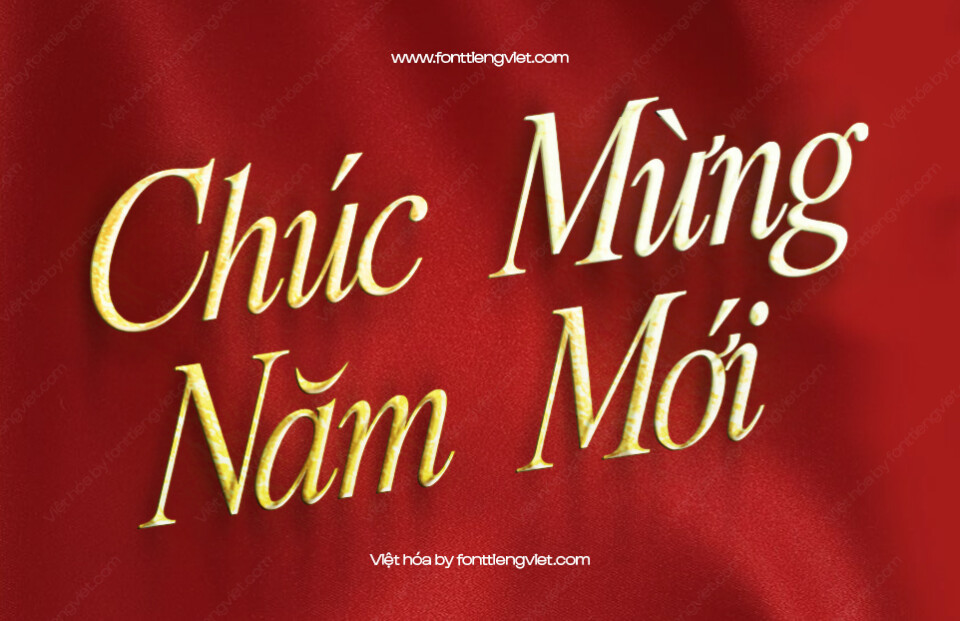
Font Việt hóa 1FTV VIP Relationship Of Mélodrame – Tết
Giới thiệu bộ Font Việt hóa 1FTV VIP Relationship Of Mélodrame – Tết
Chào mừng bạn đến với thế giới sáng tạo của những con chữ đầy nghệ thuật và cảm xúc. Trong không khí rộn ràng chuẩn bị cho mùa xuân mới, nhu cầu tìm kiếm những bộ Font Miễn Phí chất lượng cao luôn là ưu tiên hàng đầu của các nhà thiết kế đồ họa. Bộ Font Việt hóa 1FTV VIP Relationship Of Mélodrame – Tết chính là món quà đặc biệt dành riêng cho cộng đồng thiết kế Việt Nam. Đây không chỉ là một phông chữ thông thường mà là sự kết hợp hoàn hảo giữa nét cổ điển thanh lịch và tinh thần hiện đại đầy sức sống. Với các đường nét được chăm chút tỉ mỉ, bộ font này giúp truyền tải thông điệp về sự gắn kết, tình yêu và những giá trị truyền thống tốt đẹp trong dịp Tết Nguyên Đán.
Đặc điểm nổi bật của Font Việt hóa 1FTV VIP Relationship Of Mélodrame – Tết
Thiết kế sang trọng và mang tính biểu tượng
Bộ Font Việt hóa 1FTV VIP Relationship Of Mélodrame – Tết sở hữu cấu trúc chữ cái mảnh mai nhưng vô cùng chắc chắn, tạo nên một cảm giác sang trọng (VIP) ngay từ cái nhìn đầu tiên. Các ký tự được thiết kế với độ tương phản cao, mô phỏng phong cách Mélodrame đầy kịch tính và lãng mạn. Điều này giúp bộ font trở nên cực kỳ nổi bật trên các ấn phẩm truyền thông như poster sự kiện, bìa tạp chí hoặc các thiệp chúc mừng năm mới. Đặc biệt, các dấu câu tiếng Việt đã được tinh chỉnh lại một cách khéo léo, đảm bảo không bị lỗi font khi gõ văn bản dài, giúp quy trình làm việc của bạn trở nên trơn tru và chuyên nghiệp hơn bao giờ hết.
Tính ứng dụng đa dạng trong mùa lễ hội
Khả năng thích ứng của Font Việt hóa 1FTV VIP Relationship Of Mélodrame – Tết là rất ấn tượng. Bạn có thể sử dụng nó cho các tiêu đề chính của banner quảng cáo Tết, các bao lì xì mang phong cách tối giản hay thậm chí là các video giới thiệu sản phẩm xuân. Font chữ này mang lại sự hài hòa khi kết hợp với các gam màu truyền thống như đỏ, vàng và xanh lá, tạo nên một không gian thị giác ấm cúng và đoàn viên. Sự tinh tế trong từng nét chữ giúp người xem cảm nhận được sự chân thành và tinh thần gắn kết đúng như tên gọi Relationship của bộ phông chữ này.
Hướng dẫn sử dụng và tối ưu thiết kế với font chữ Tết
Cách phối hợp màu sắc và bố cục
Để phát huy tối đa vẻ đẹp của Font Việt hóa 1FTV VIP Relationship Of Mélodrame – Tết, bạn nên ưu tiên các bố cục thoáng đãng và sử dụng khoảng trắng thông minh. Việc đặt font chữ này lên các nền hình ảnh có độ chi tiết thấp sẽ giúp các nét chữ thanh mảnh được hiển thị rõ nét nhất. Đối với các thiết kế in ấn, hãy thử sử dụng kỹ thuật ép kim hoặc phủ UV trên các ký tự chính để tạo hiệu ứng thị giác đẳng cấp. Đừng quên rằng sự đơn giản chính là chìa khóa để làm nổi bật nét đẹp nghệ thuật của phong cách Mélodrame trong thiết kế hiện đại.
Kết luận về bộ Font Việt hóa 1FTV VIP Relationship Of Mélodrame – Tết
Sở hữu bộ Font Việt hóa 1FTV VIP Relationship Of Mélodrame – Tết trong thư viện thiết kế của mình sẽ giúp bạn tự tin hơn trong việc tạo ra những tác phẩm ấn tượng cho mùa Tết 2026. Với sự tinh tế trong đường nét và ý nghĩa nhân văn về sự gắn kết, đây chắc chắn là lựa chọn không thể bỏ qua. Hãy nhanh tay truy cập và tải ngay bộ Font Miễn Phí, Font Việt Hóa, Font Việt hóa 1FTV VIP Relationship Of Mélodrame – Tết để bắt đầu hành trình sáng tạo những ấn phẩm tuyệt vời nhất cho mùa xuân này. Chúc bạn có những trải nghiệm thiết kế đầy cảm hứng và thành công rực rỡ với các dự án sắp tới của mình.